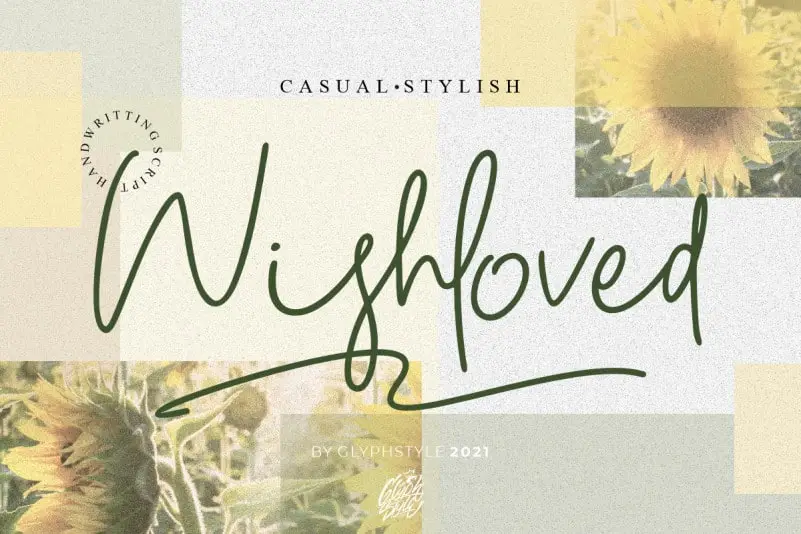
A ‘Wishloved Handwritten Font’ é uma elegante fonte escrita a mão que transmite casualidade e estilo moderno. Perfeita para qualquer uso visual, este recurso gráfico oferece movimentos de traço natural que transformam texto simples em arte exuberante e delicada. Ideal tanto para capas de livros quanto para logos, ou até mesmo como fonte para nomear seus produtos e marcas, a ‘Wishloved Handwritten Font’ é perfeitamente ajustada para se juntar a qualquer projeto que deseje dar um toque pessoal e sofisticado. Com sua natureza fluida e encantadora, essa fonte escrita a mão oferece uma maneira única de personalizar seus materiais impressos ou digitais, tornando-os únicos e envolventes.